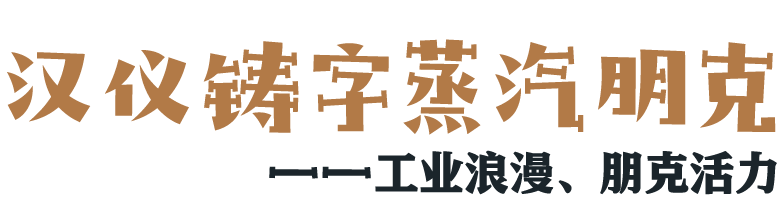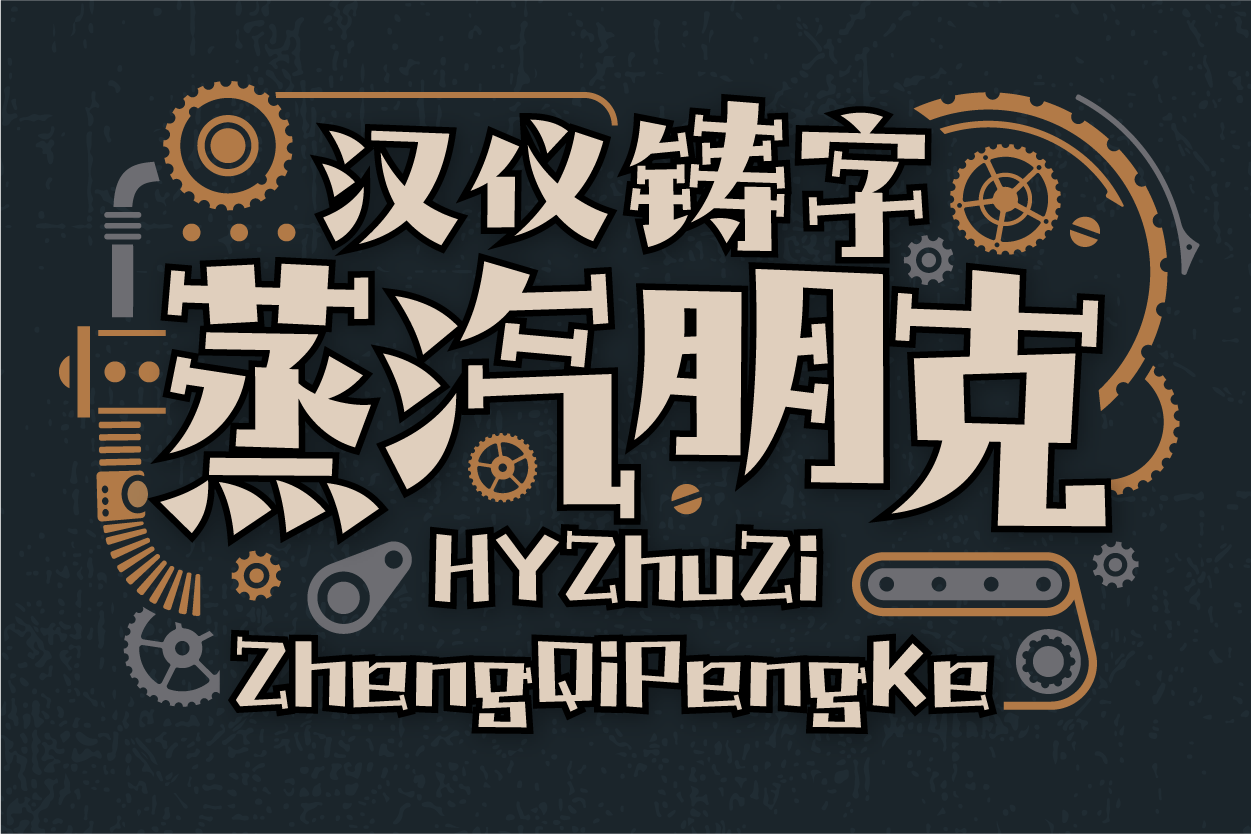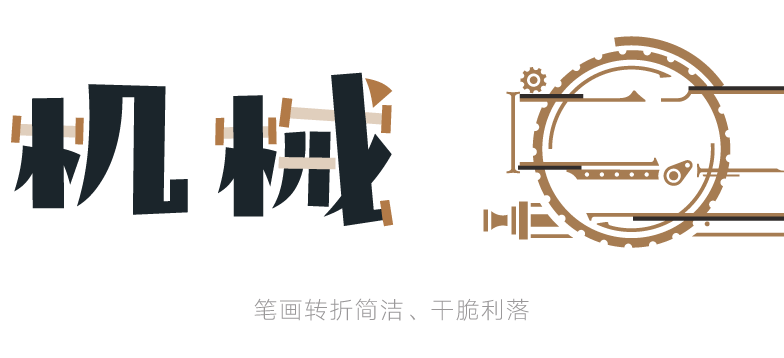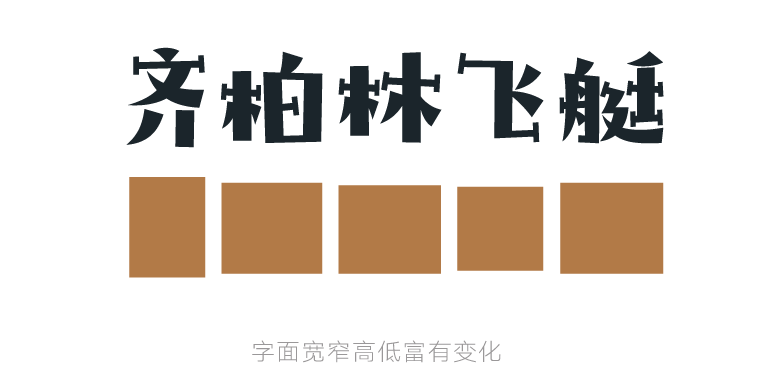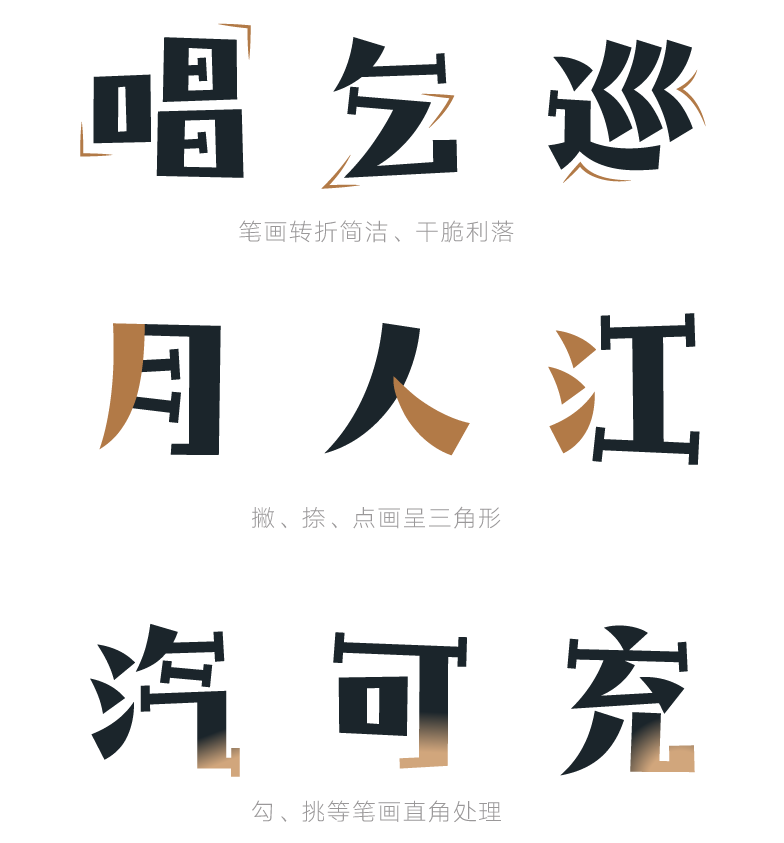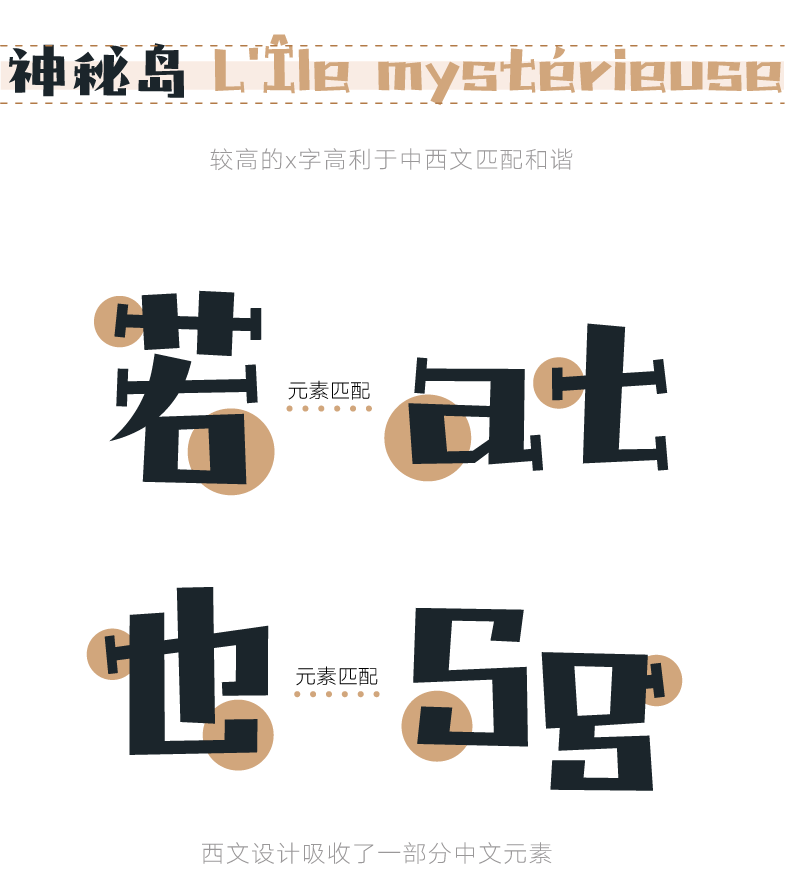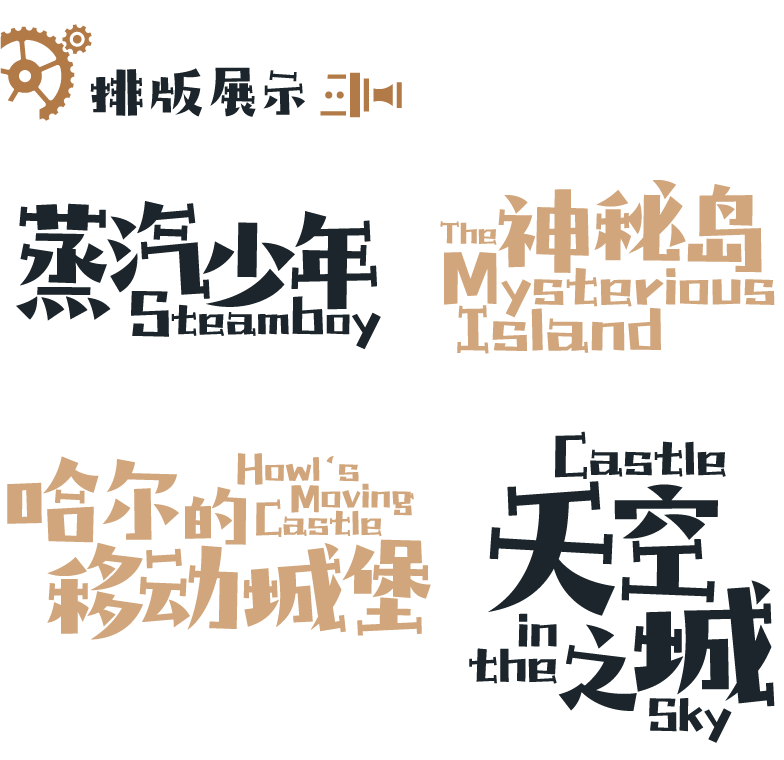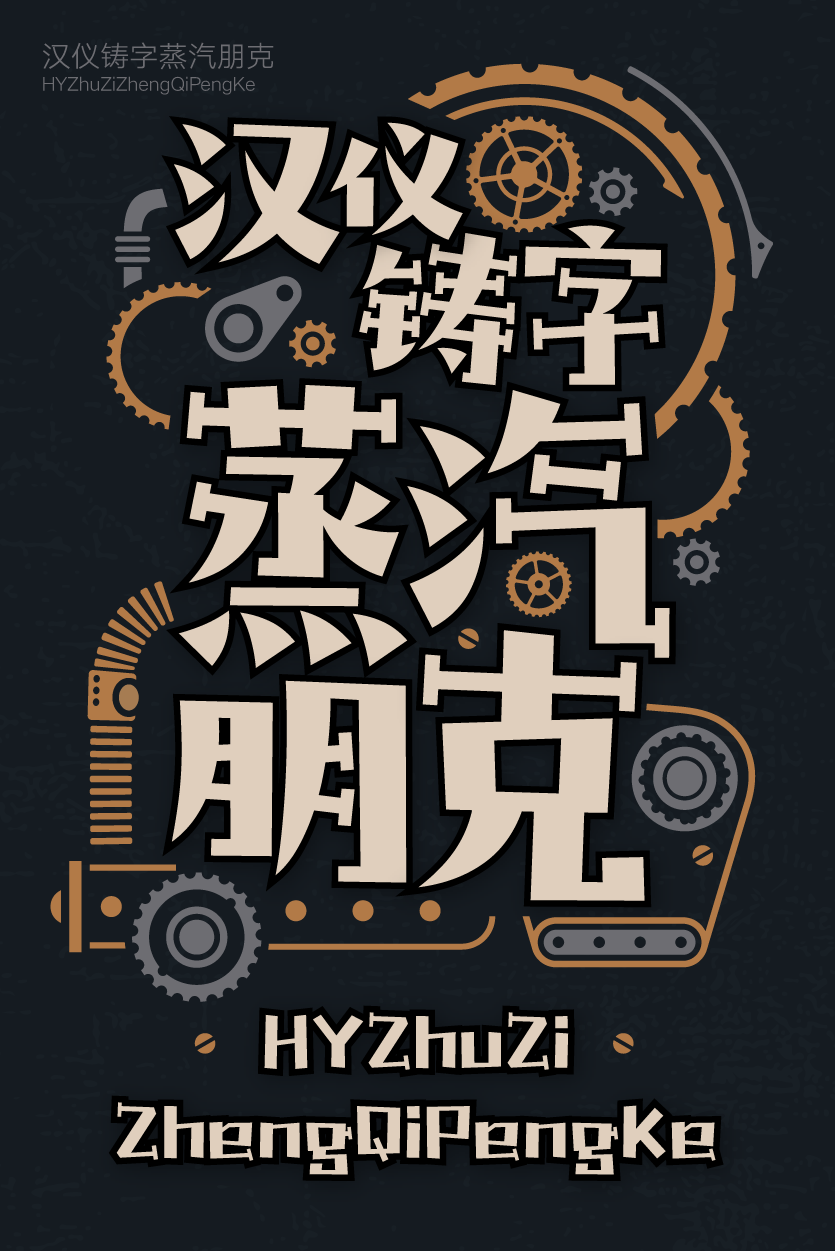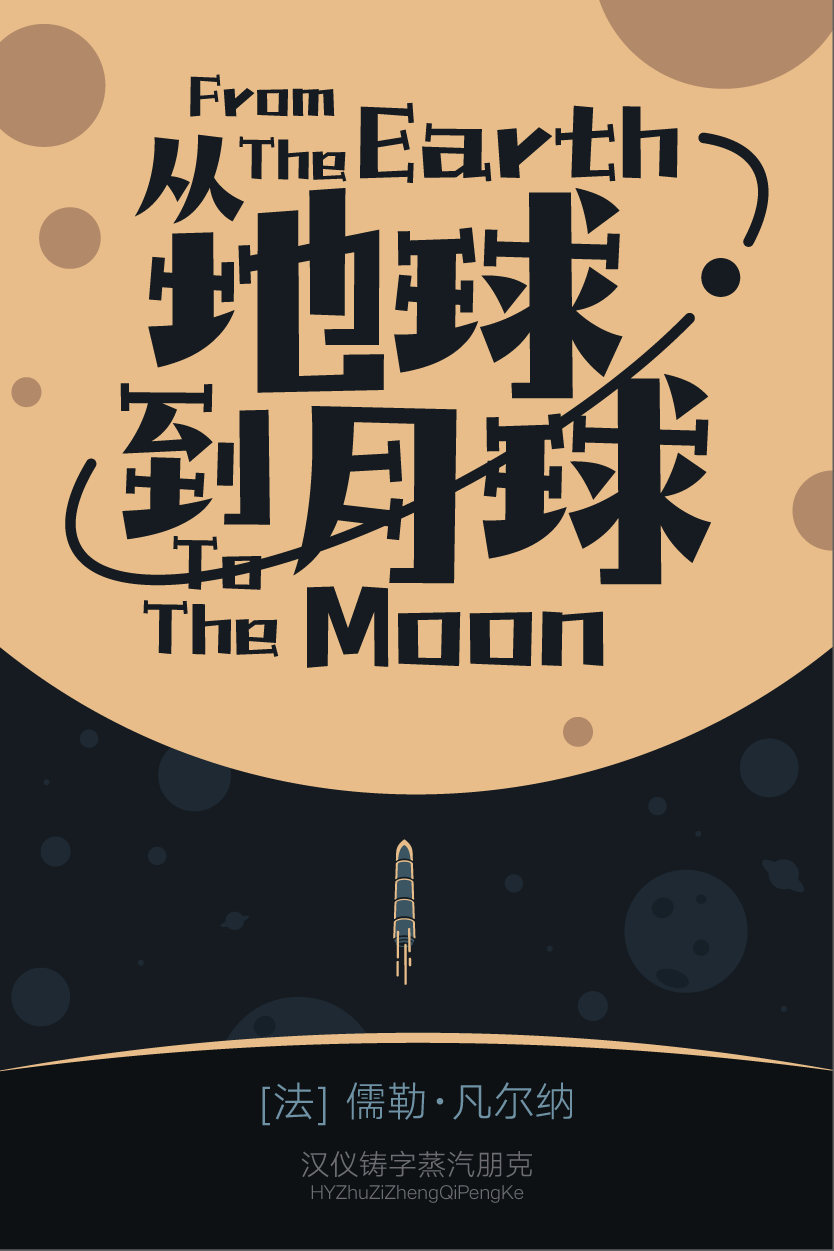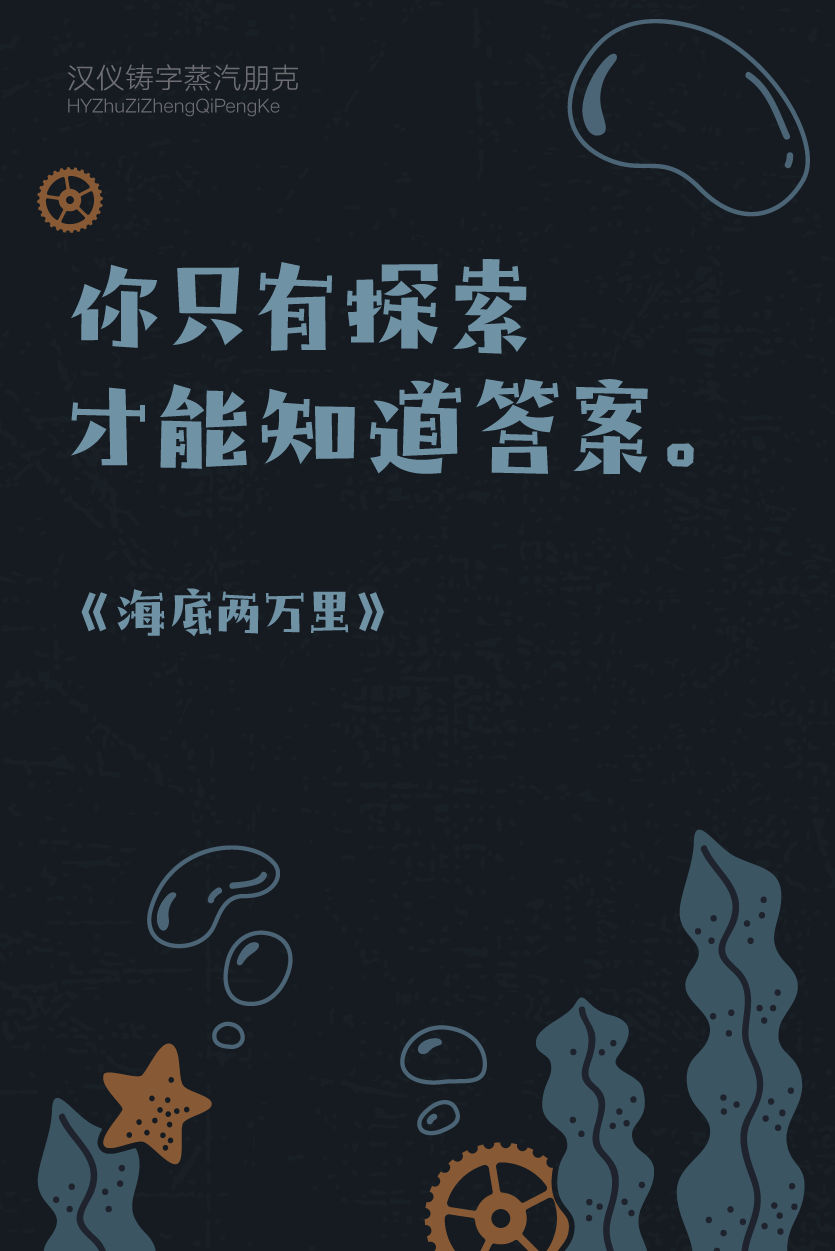
汉仪铸字蒸汽朋克字体介绍,汉仪铸字蒸汽朋克设计灵感
工业 / 怀旧 / 天真 / 叛逆 / 活力 / 乐观 / 可爱
标志 / 书籍 / 广告 / 杂志 / 游戏 / 动漫 / 影视 / 包装
汉仪铸字蒸汽朋克是一款兼具朋克文化的叛逆气息与工业革命的科技浪漫的创意设计字体。整体风格乐观,叛逆、怀旧、可爱,适合作为标题字,用在绘本玩具、文创周边、综艺影视等场合。
汉仪铸字蒸汽朋克这款字横细竖粗,横画两端有着螺丝帽一样的装饰衬线,增添机械装置的印象。
该字体结构轻松不羁,每个笔画都成一定角度倾斜,字面也随着字形结构的变化而有轻微的宽窄高低的波动,带来蒸汽科技的动力感,和爵士乐一样的怀旧韵律感。
这款字的笔画设计干净利落:笔画基本由线段组成,转折简洁无装饰,撇、捺、点画呈三角形锐利充满叛逆感,勾、挑直角处理为字形增添趣味性。
这款字的西文部分设计参考了中文的设计思路,字形全部采用直线设计,每一笔都有一定的倾斜,并在字形中增添螺母装饰,使得字形看起来俏皮可爱。中西文排版后和谐统一。